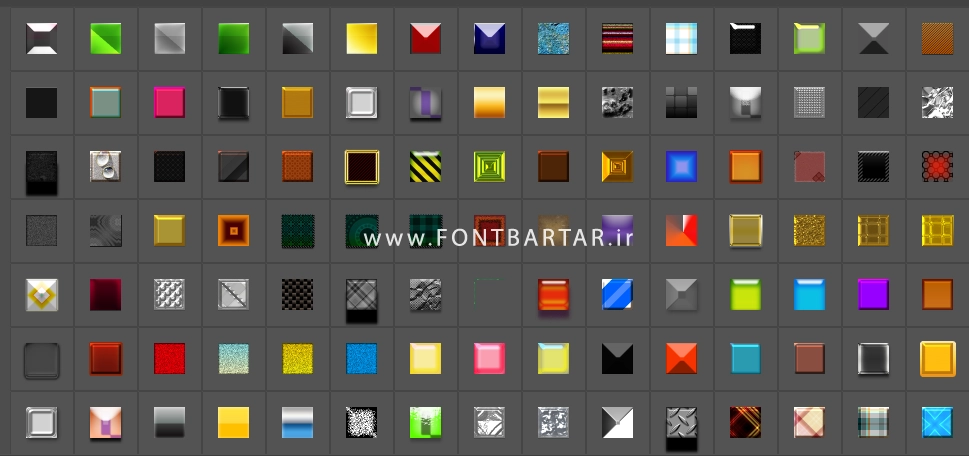
دانلود تکست استایل فتوشاپ | بیش از 100 استایل آماده و حرفهای
تکست استایل برای فتوشاپ اگر شما هم از علاقهمندان به طراحی گرافیک در فتوشاپ هستید، حتماً میدانید که داشتن یک مجموعه کامل از تکســت استایلهای آماده میتواند سرعت کار شما را چندین برابر کند. تکست استایل در این صفحه میتوانید بیش از 100 تکست استایل فتوشاپ را به صورت یکجا و کاملاً رایگان دانلود کنید.
چرا باید از تکست استایل فتوشاپ استفاده کنیم؟
تکست استایل فتوشاپ از تنظیمات از پیش ساخته شده هستند که روی متن اعمال میشوند و باعث میشوند نوشتهها جلوهای خاص و حرفهای به خود بگیرند. به جای اینکه ساعتها وقت خود را صرف طراحی افکت متن کنید، کافی است تنها با یک کلیک استایل دلخواهتان را روی نوشته اعمال کنید.
ویژگی های تکست استایل فارسی :
- بیش از 100 تکست استایل متنوع (طلایی، نقرهای، متالیک، سهبعدی، گلیچ، سایهدار و …)
- تکست استایل یوتیوب
- کیفیت بالا و قابل استفاده در طراحی لوگو، پوستر، کارت ویزیت، بنر تبلیغاتی و شبکههای اجتماعی
- طراحی سریع لوگو تایپهای حرفهای
- ساخت کاور اینستاگرام و یوتیوب
- استفاده در پوسترهای تبلیغاتی و چاپی
- جذابتر کردن تایپوگرافی فارسی و انگلیسی